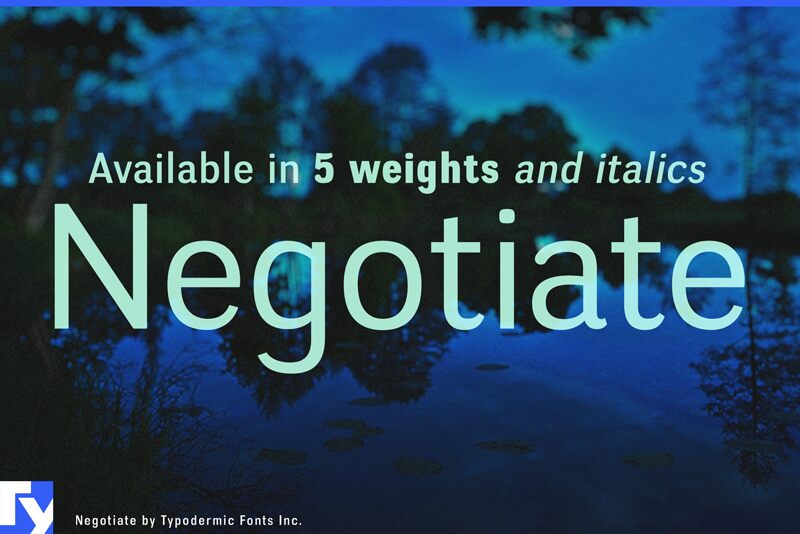
Negotiate kombinuje profesionální vyrovnanost s lidským teplem prostřednictvím zaoblených tahů a čtvercových zakončení, které vyvažují přístupnost a strukturu. Její otevřené proporce a jemný kontrast dodávají textu přehlednost a titulkům osobitost. Pět řezů včetně kurzív nabízí flexibilitu; od lehkého, vytříbeného tělového textu až po výraznou, sebevědomou nadpisovou sazbu, zatímco starožitné číslice dodávají klasickou sofistikovanost. Písmo navržené pro značky, publikace a značení, které si cení kredibility s charakterem, vyzařuje jistotu bez chladu a poskytuje čitelnost a sofistikovanost ve stejné míře.
Prezentace a vizuální ukázka písma Negotiate Regular